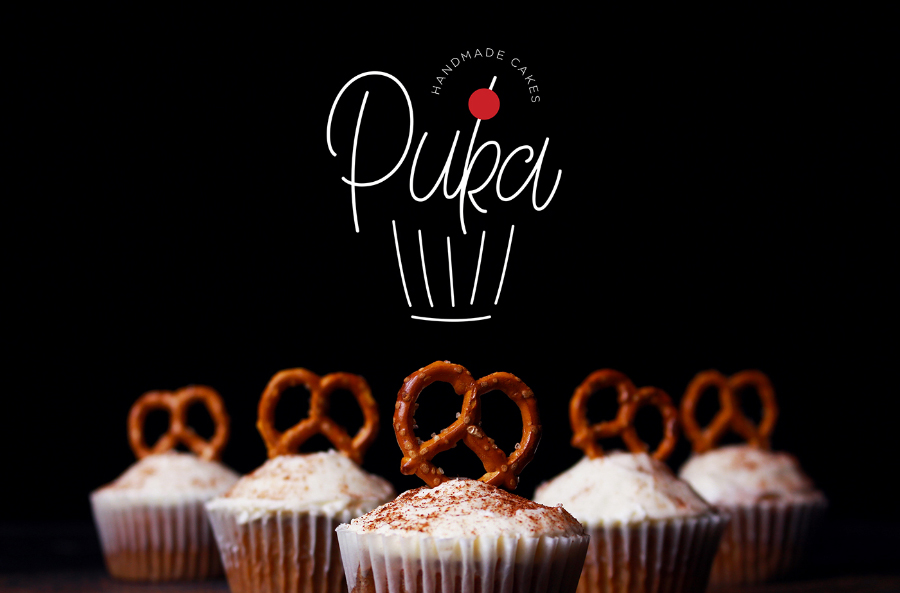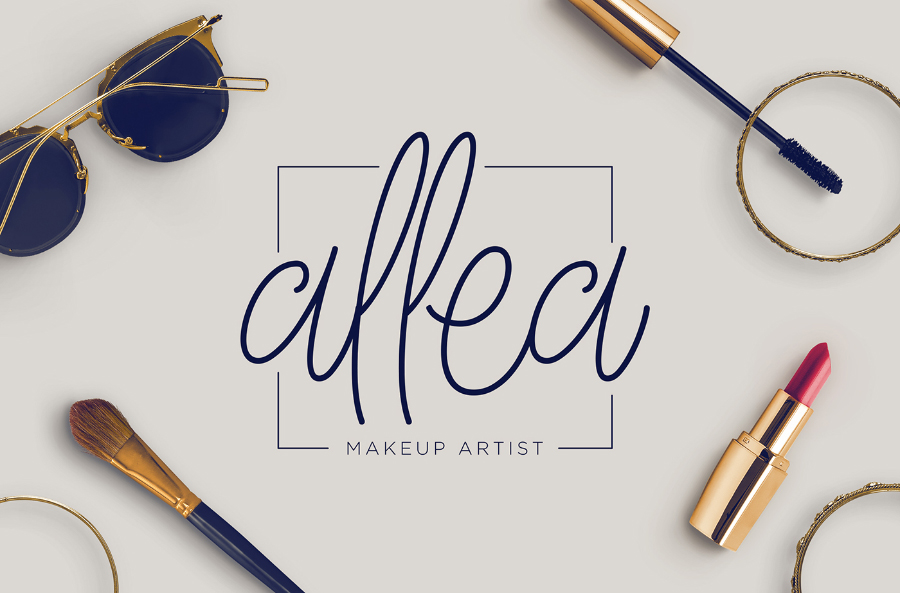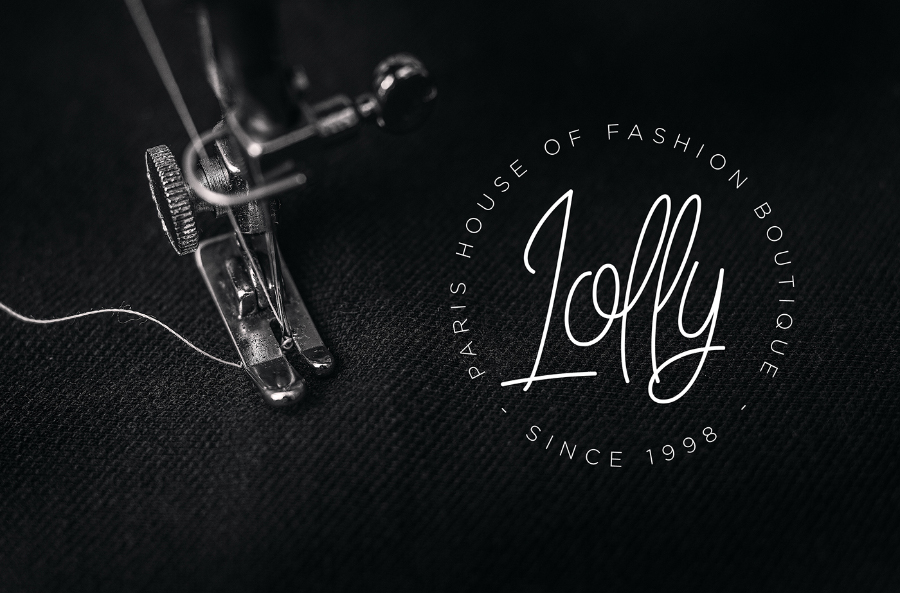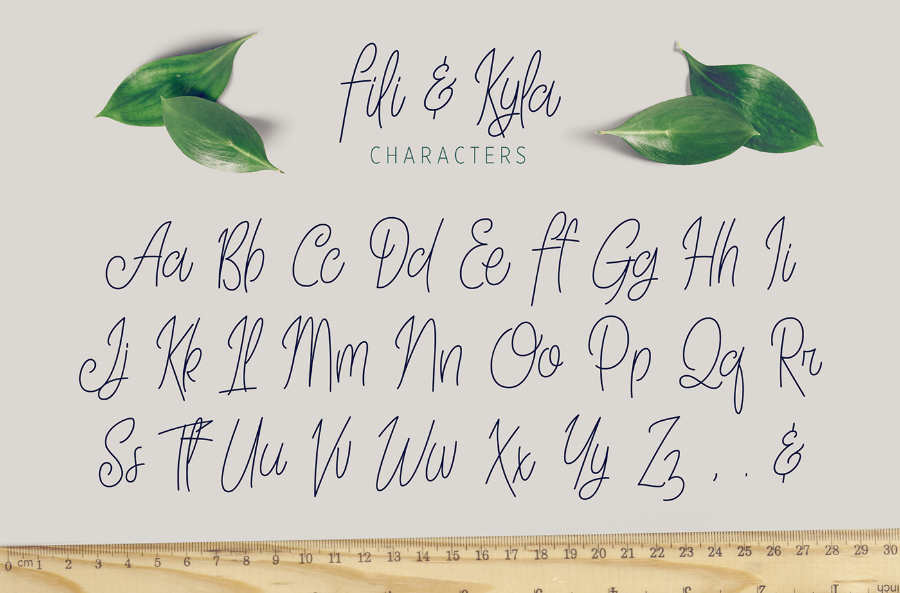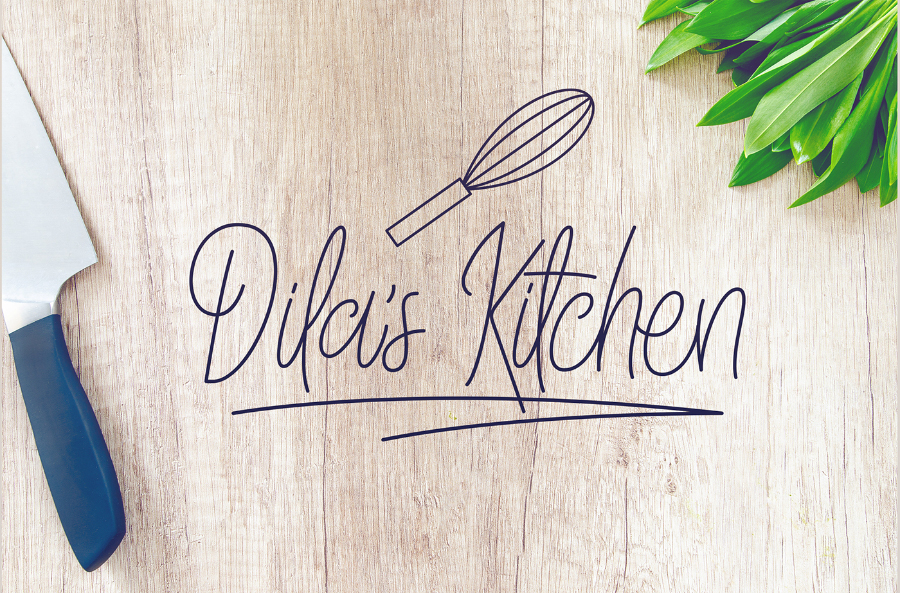
Fili&Kyla Monoline免费字体
Fili & Kyla Monoline Free Font
请欢迎,Fili&Kyla Monoline免费字体。你真正的手写monoline女性脚本字体。它是优雅的,曲线和旋转自然。因此,这种字体将完全适合你的休闲品牌的东西。也非常适合女性和美丽的标志类型,以及更多。